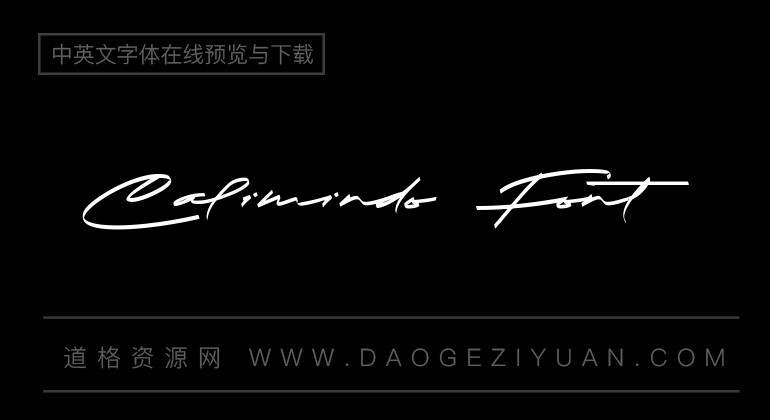
Calimindo Font 是一种优美的手写风格字体,设计师Fikry Alif在 2019 年创作,该字体包括字母,数字和标点符号,并可用于商业和个人项目。 Calimindo Font 的整体风格轻盈、流畅,具有一定的艺术感和独特性。字母间距适中,字母形状流畅,可以在海报、名片、书籍、广告、应用程序和网站等多种设计场景中使用。此外,Calimindo Font 还包括了多种语言支持,如西班牙语、法语和德语等,因此可以满足多种语言环境的需求。 总的来说,Calimindo Font 是一种非常美丽和实用的字体,适合于多种设计场景。内容介绍
Calimindo Font是一款非常不错的手写艺术字体,具有很好的视觉感,适合于文化类的宣传设计、商业类品牌的广告和产品包装设计以及个性化文字排版等较多场景。